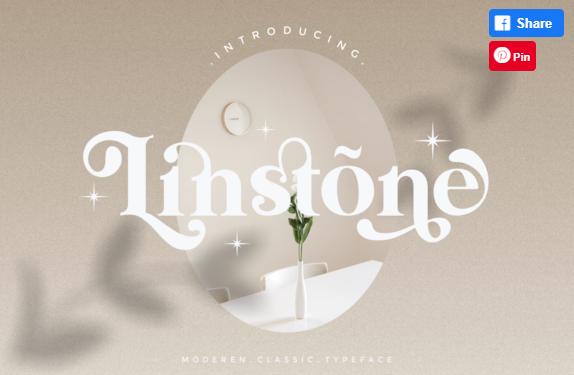
[Creativefabrica] Linstone Font (Penatic Studio)
Linstone - современный, элегантный и смелый шрифт с засечками. Этот шрифт отличается аккуратностью и высокой детализацией. Linstone закодирован PUA, что означает, что вы можете легко получить доступ ко всем глифам и штрихам!